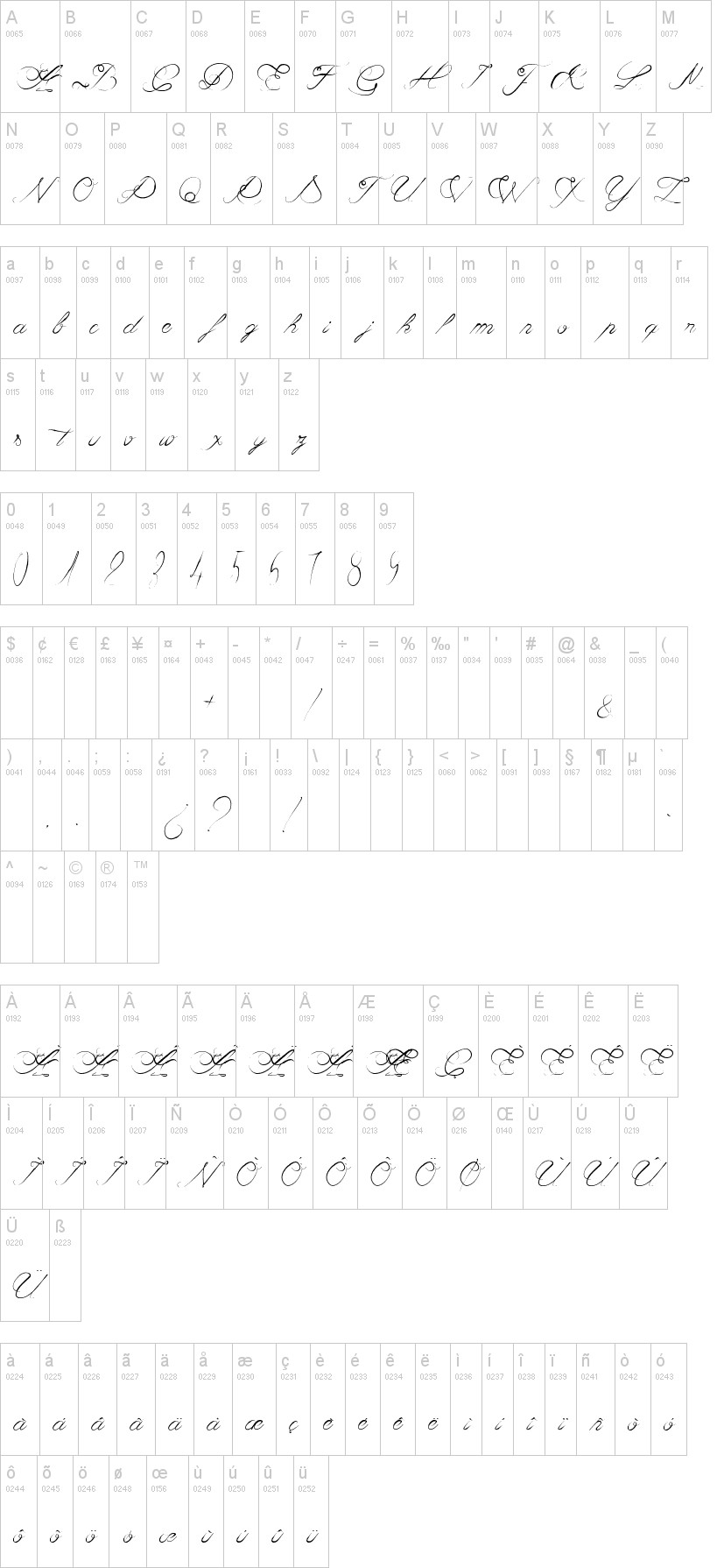
Caviar de Diane
Caviar de Diane 是一款经典的手写字体,具有非常优美的卷曲线条和精致的笔画。它是由设计师 Lauren Thompson 创建的,旨在呈现出女性的优雅和精致。 这种字体的特点是它的字母间距非常小,因此在排版时会产生一种密集的感觉,同时字母的形状和线条相当流畅,每个字母都带有一些独特的装饰元素。Caviar de Diane 字体用于设计印刷品、包装、品牌标识等需要体现高贵和精致的场景。 总体来说,Caviar de Diane 字体是一款非常优美、精致、适用于多种设计场景的字体。
Caviar de Diane是一款非常不错的手写艺术字体,具有很好的视觉感,适合于文化类的宣传设计、商业类品牌的广告和产品包装设计以及个性化文字排版等较多场景。